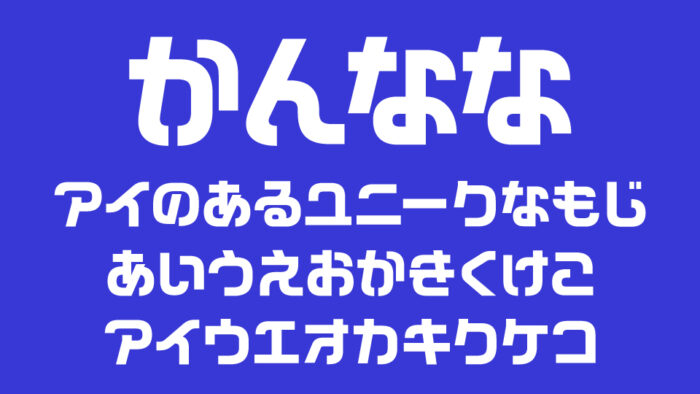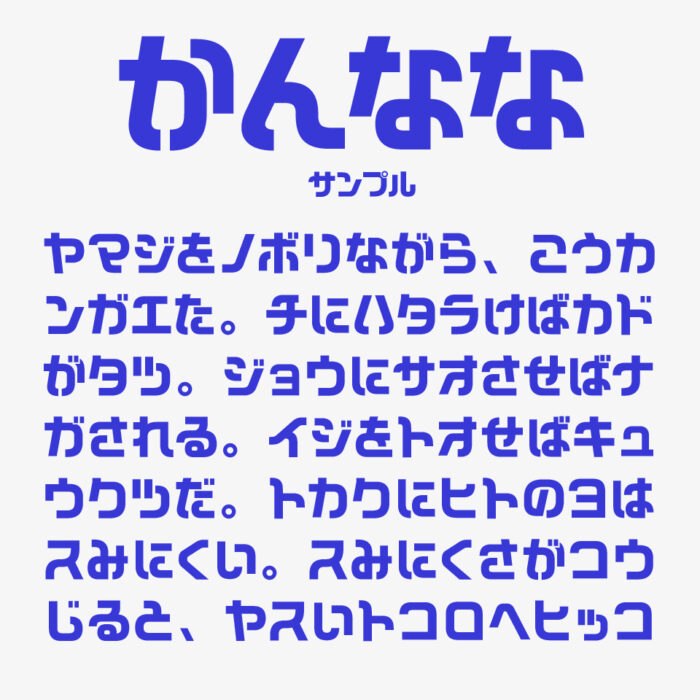
かんなな
かんななフォントは、太めでどっしりとした線に、少しクセのある丸みフォルムを組み合わせた存在感の強いデザインかなフォントです。
文字が津繋がりそうなユニークな角を丸く落とした処理が、親しみやすさと遊び心が散りばめられているデザインです。文字の一つひとつにリズムが感じられるため、ポップさと安定感を同時に楽しめるフォントとなっています。
かんなな
収録文字は、ひらがな・カタカナ・一部記号が収録されています。
漢字×